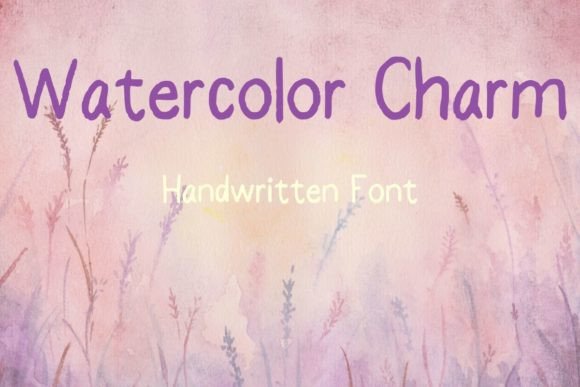
Watercolor Charm
適切なデザイン要素を見つけるのは難しい場合がありますが、Watercolor Charmは作品を即座に引き立てる優れたコレクションを提供します。
POD(オンデマンド印刷)製品、結婚式の招待状、またはソーシャルメディアのグラフィックを作成している場合でも、Watercolor Charmは理想的です。